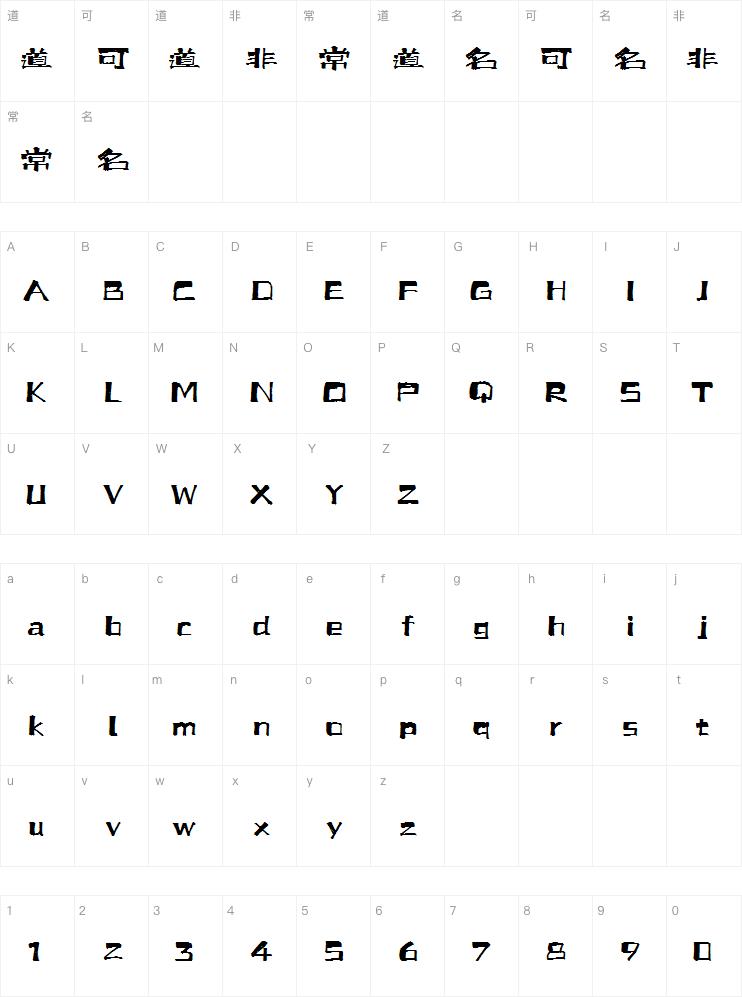
上首墨客体
上首墨客
上首墨客体,笔画粗细变化自然,兼具力量感与柔和度。起笔、收笔的提按顿挫,呈现出独特的笔触感;笔画转折处或方或圆,方折彰显刚劲,圆转蕴含柔美,丰富了字体的视觉层次。通过对字体重心的精准把握,使每个字都具有良好的平衡感;同时,字间布局疏密得当,既保证了整体的和谐统一,又增强了视觉的节奏感。通过对传统书法元素的提取与重构,使字体在视觉上保留了书法艺术的精髓,实现了对中华文化的传承与延续。适用于搭配标志、广告标语、商业广告等高端属性。
上首墨客体